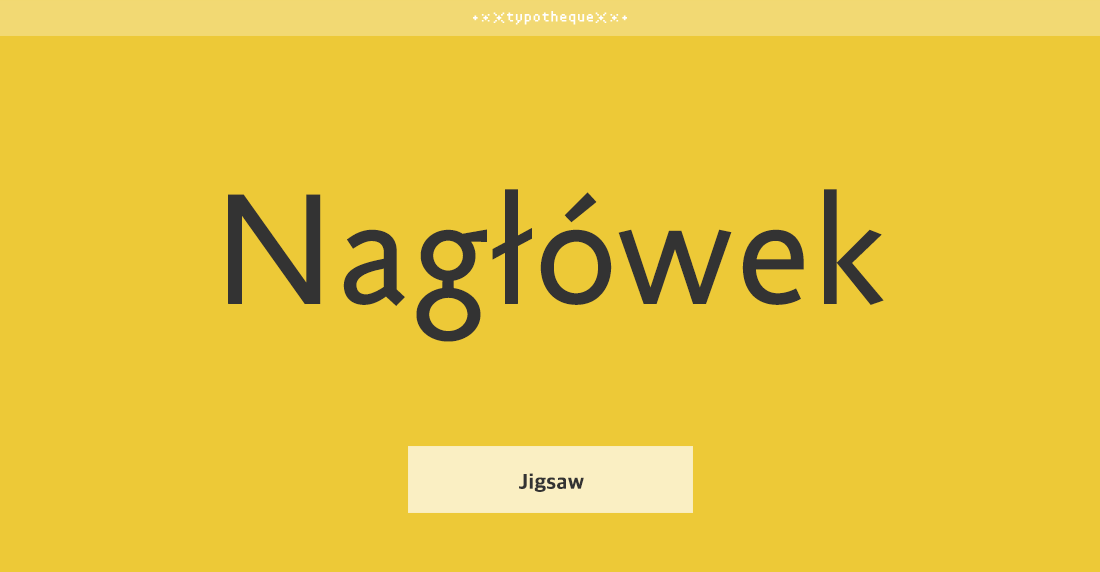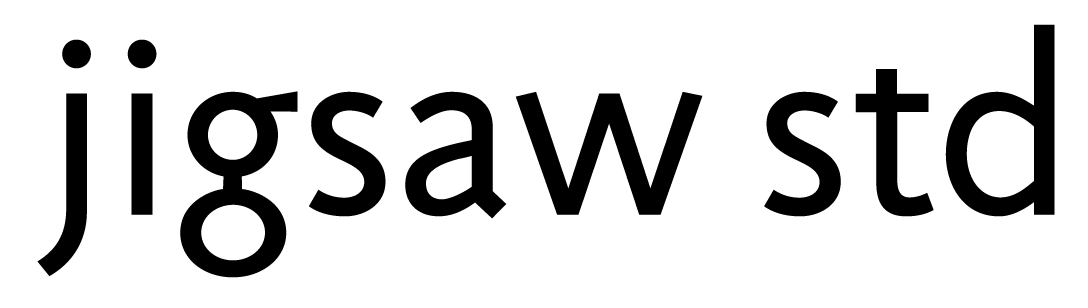
- Jigsaw Std는 수직, 수평 획의 굵기가 일정한 기하학적인 구조의 산 세리프 폰트이다.
베이직에서 파생된 Stencil버전과 주요 골격을 공유하고 있으며 4개의 웨이트를 제공한다.
폰트 정보 구분 명조 디자인디렉팅 Johanna Biľak 출시년도 2008
구분 | 명조 |
디자인디렉팅 | Johanna Biľak |
출시년도 | 2008 |